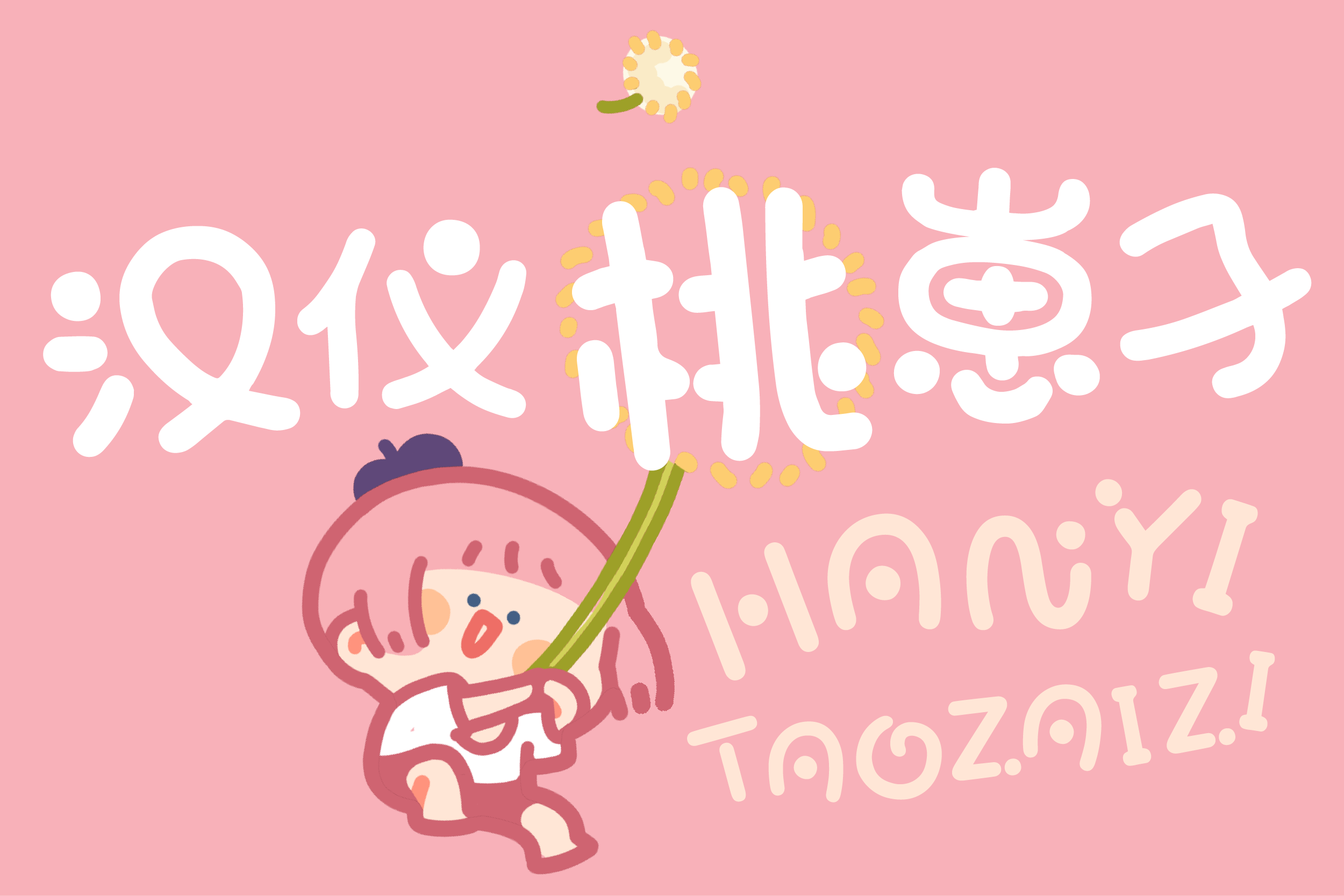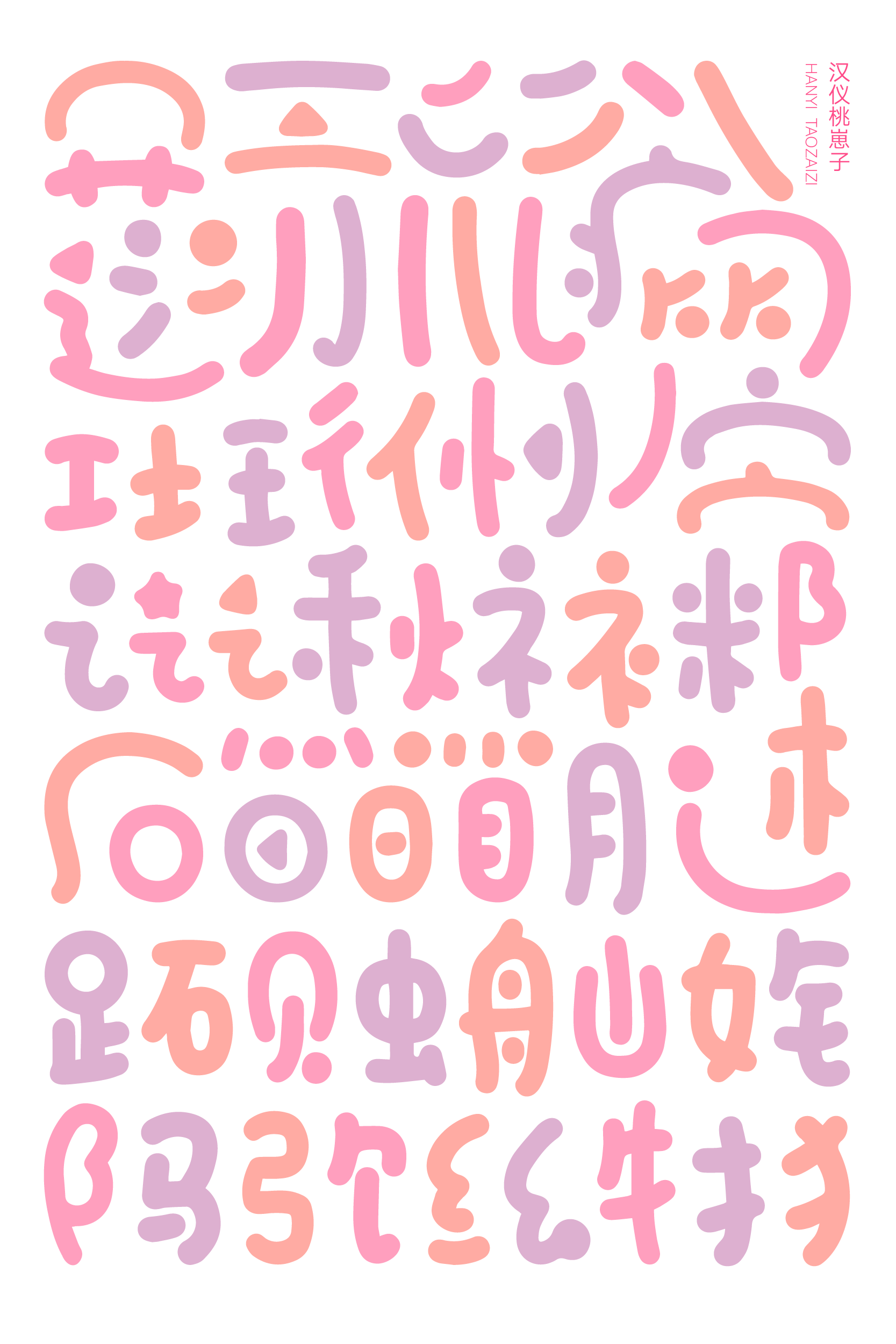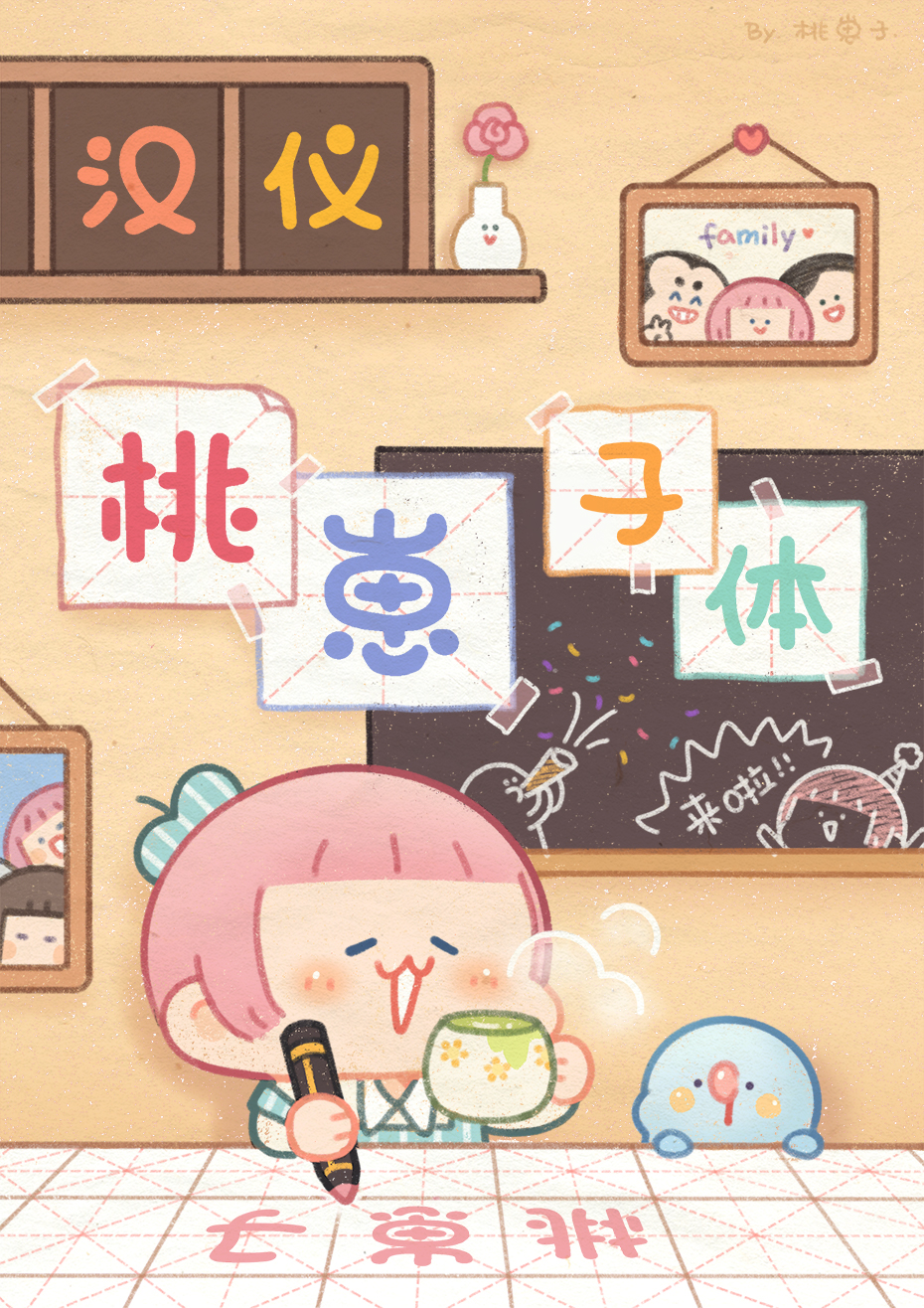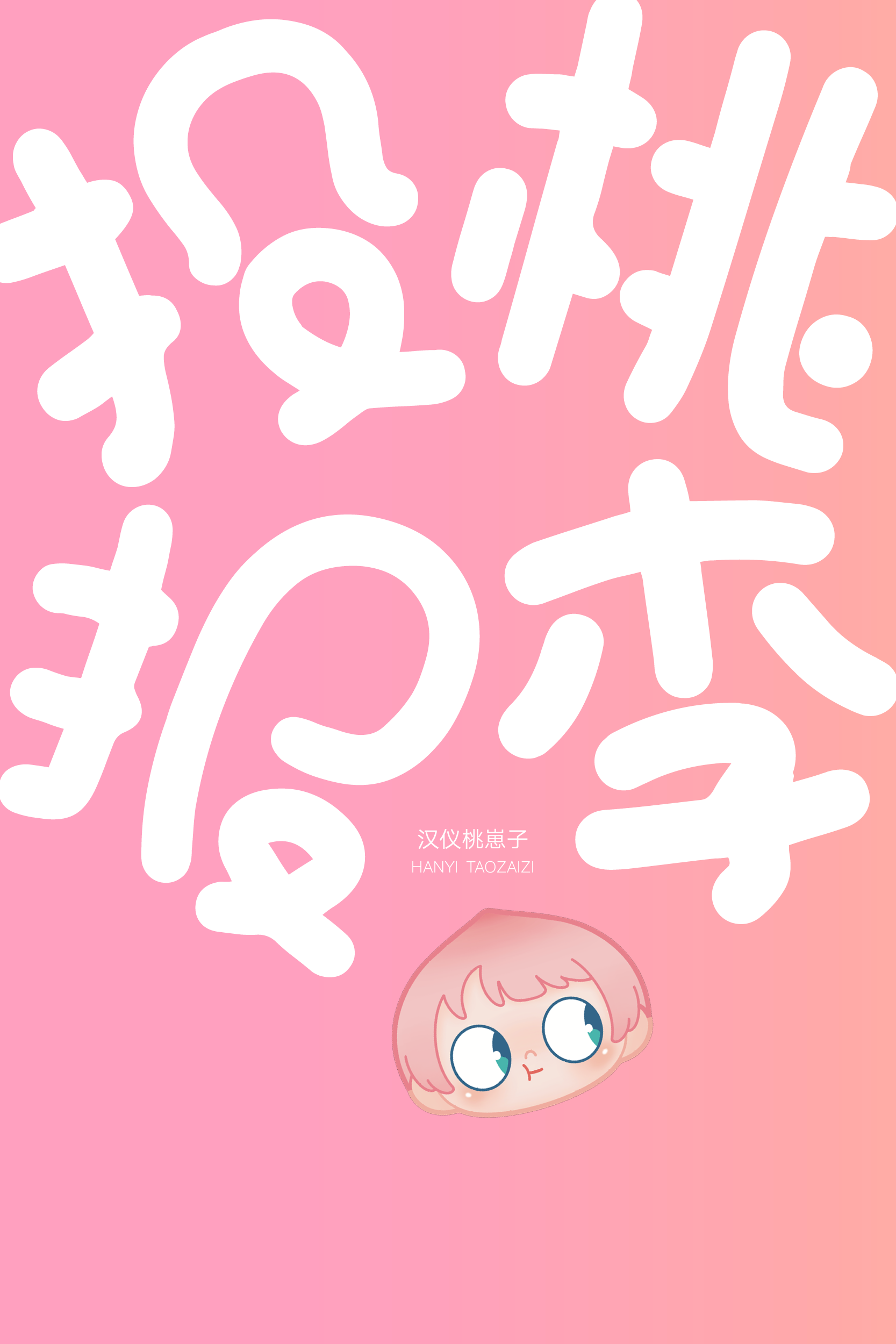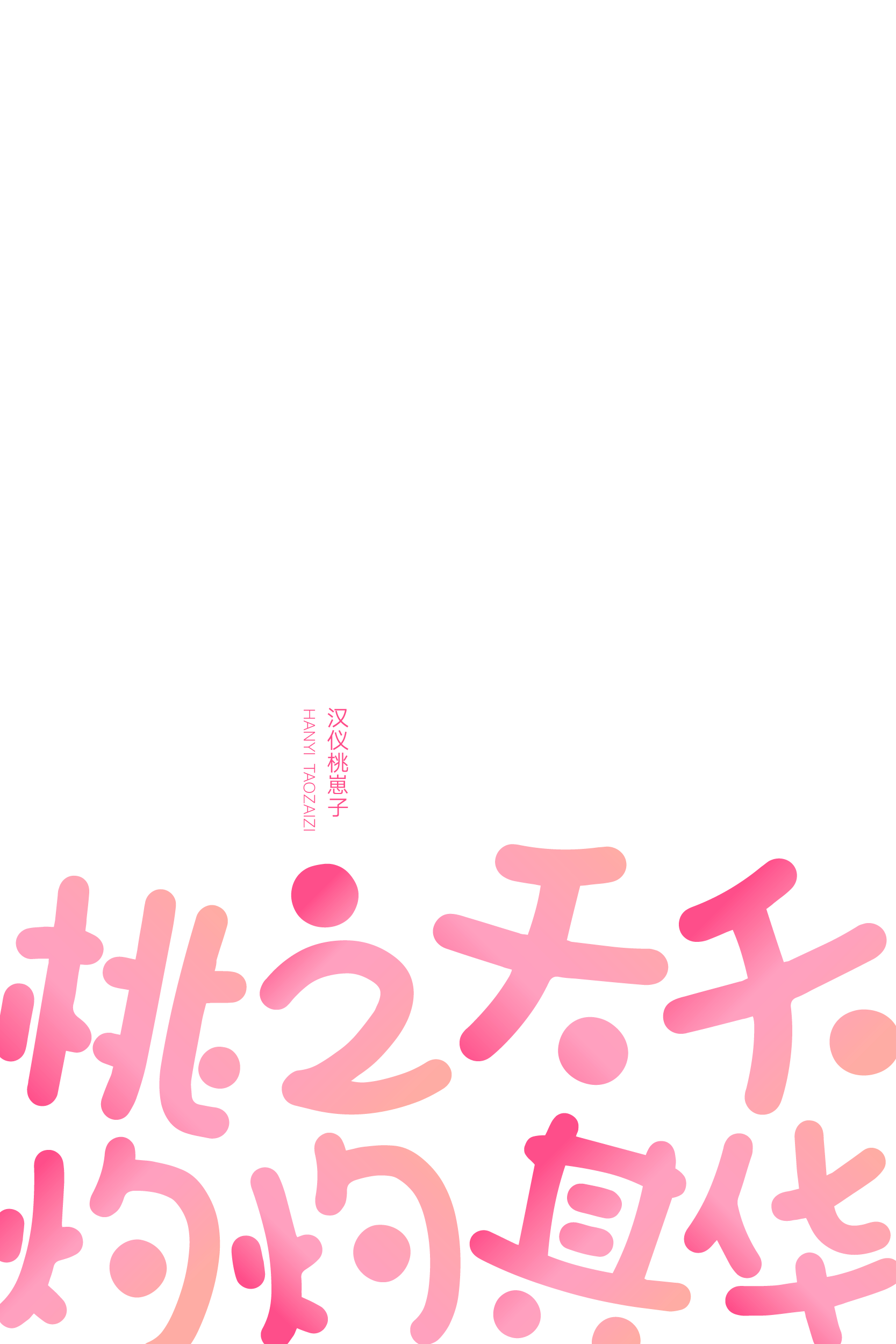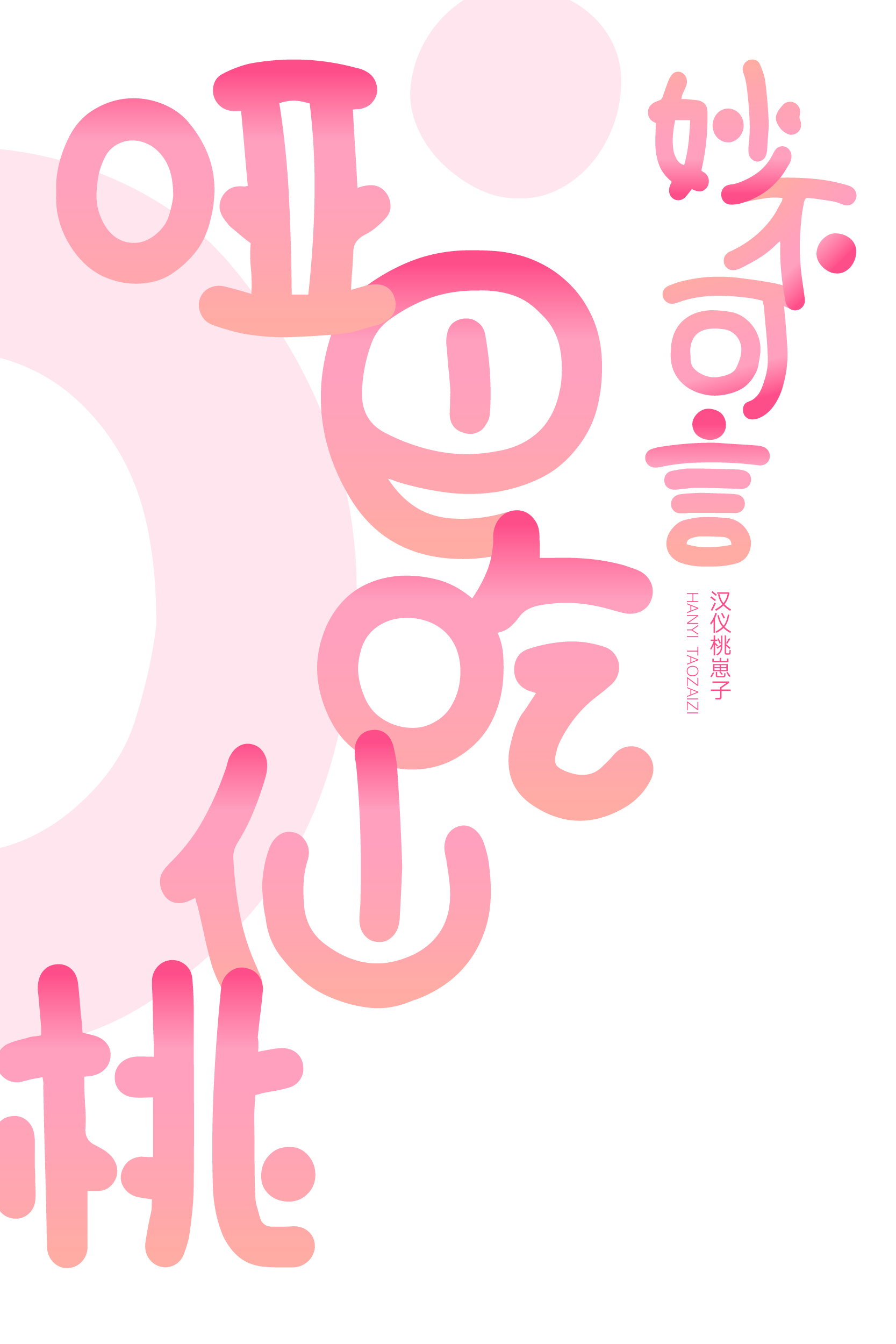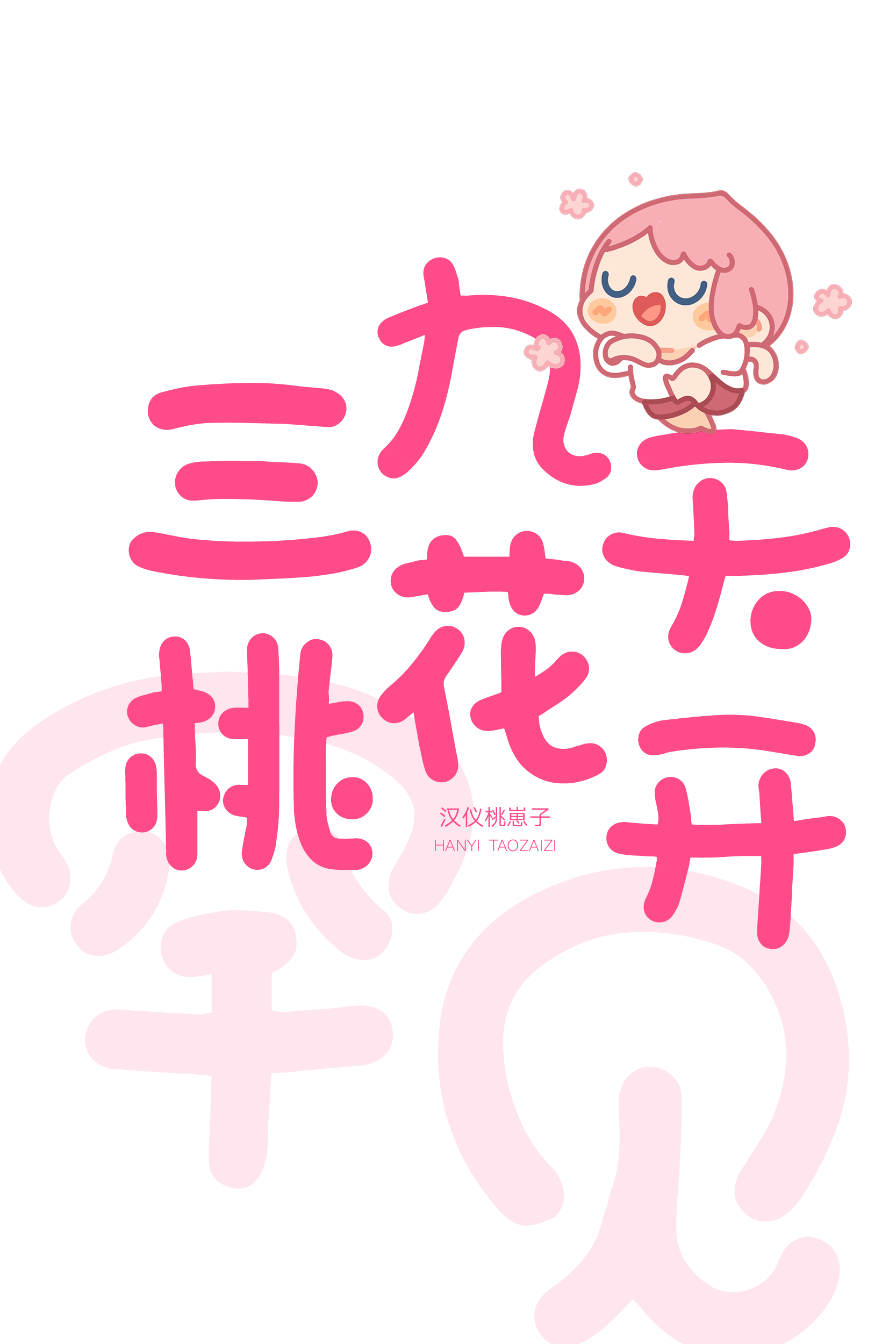
这款圆滚滚的字体,治愈了我~
汉仪桃崽子是由汉仪字库签约作者、漫画家桃崽子创作的首款字体作品。这款字体的设计源于桃崽崽圆滚滚的可爱形象,充满趣味的细节点缀其中,满满都是治愈力量和快乐能量。这款字体适合用于标题以及字数较少的文本,适合天真可爱、快乐活泼、治愈温馨的使用场景。
圆润饱满的字形和桃崽崽的形象匹配度百分百!
字形整齐而不单调,排版效果舒适活泼。
字形结构组合巧妙,布白平衡,简单的字形饱满不空洞,复杂的字形放松不拥挤。
圆乎乎的笔画化方为圆、化直为曲,消除了冷冰冰的直线和方角,充满治愈的力量。
笔画的丰富变化和图形化的部件构成了可爱的彩蛋,快来找找藏在字形中的拟态小表情吧:
“点”不只是圆形和方形,还可以是各种有趣的形态,通过笔画的细节也可以发射快乐能量!
汉仪桃崽子的西文设计同样圆润可爱,字形饱满,中西文匹配可以应用于更广泛的使用场景。
大写字母的部分横画和笔画连接处减省为圆点,增加了跃动感。同时字母和数字的设计加入了弯曲的装饰细节,趣味多多。